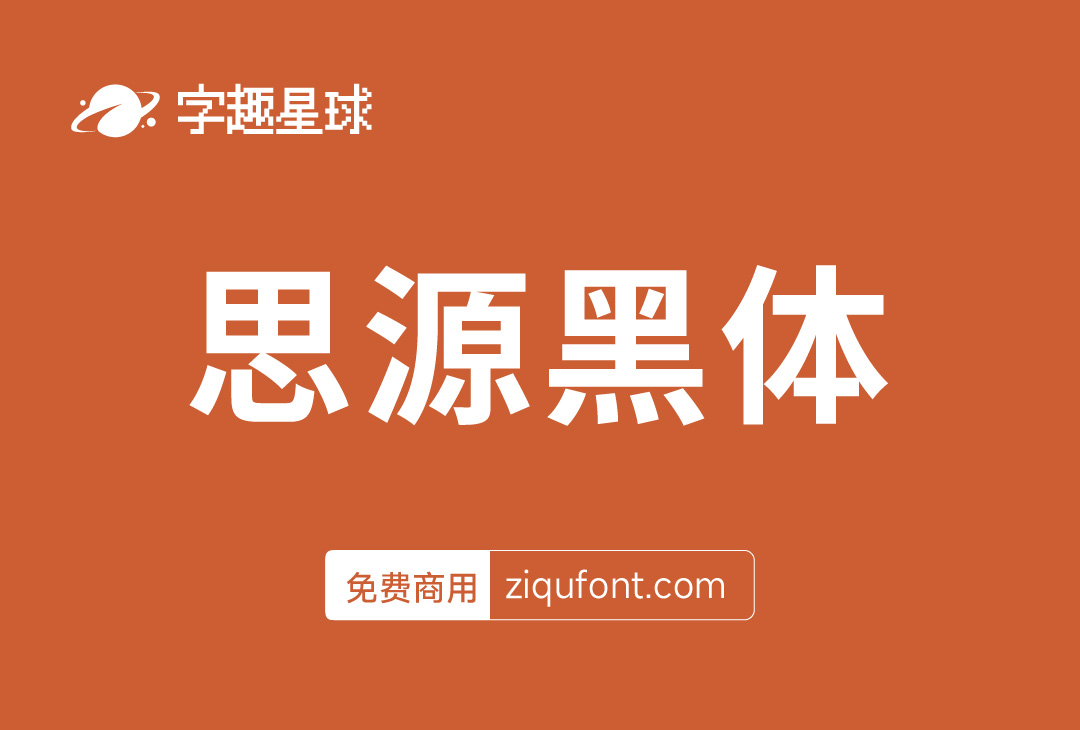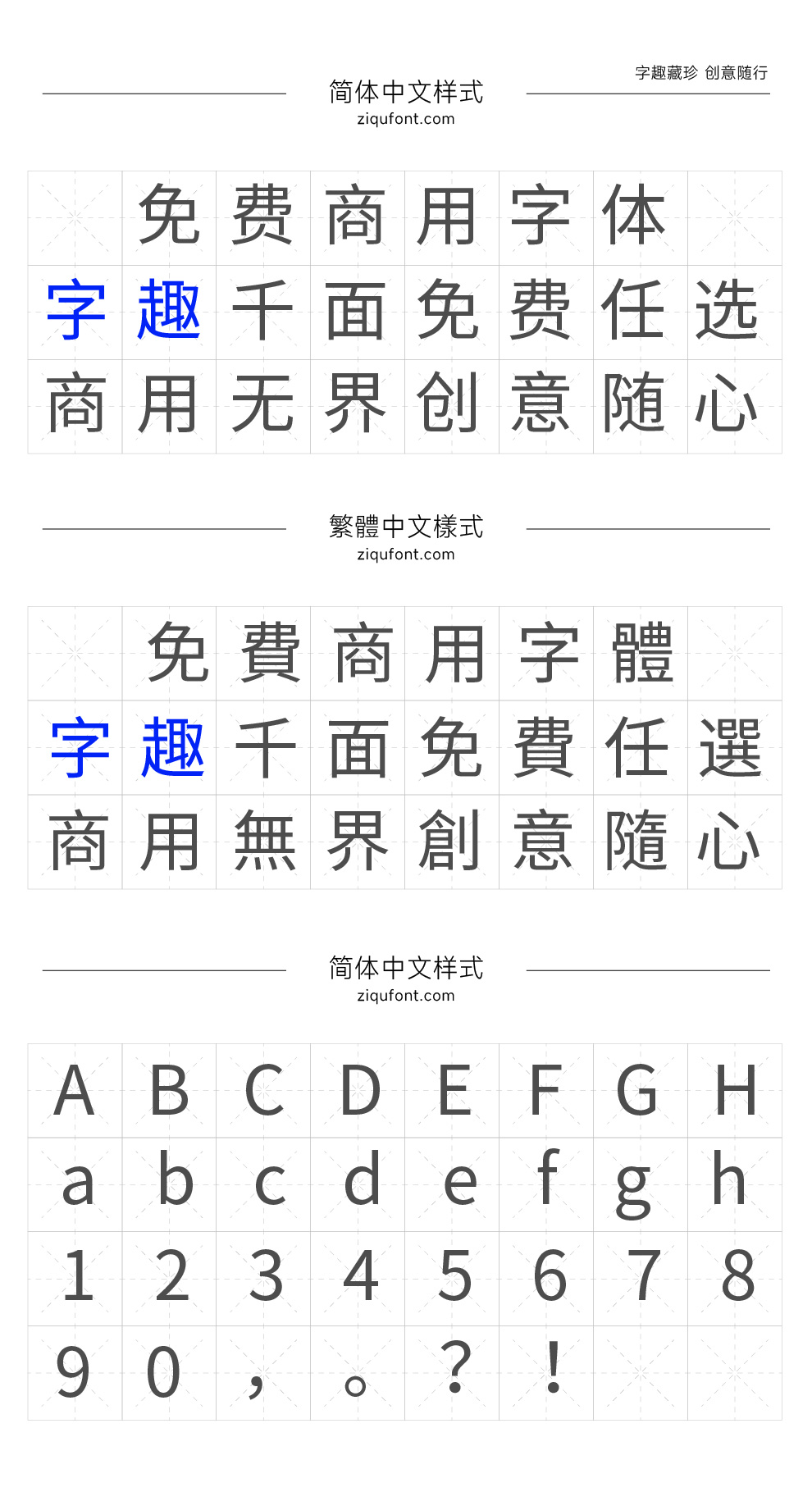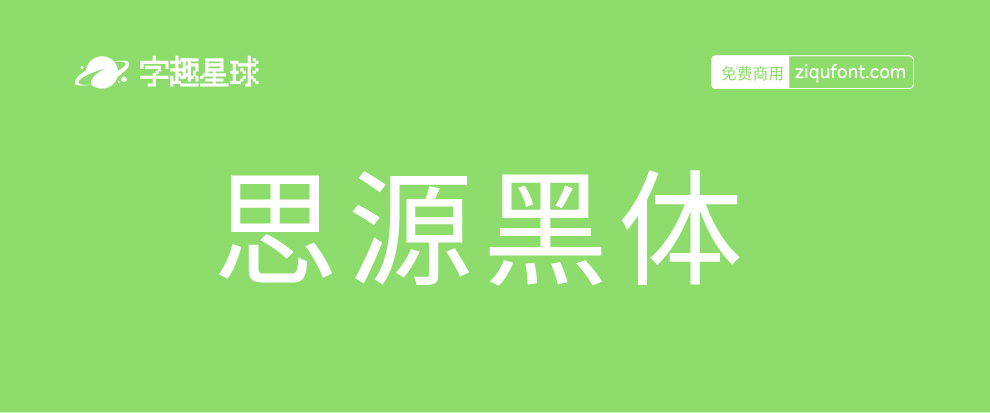
可变思源黑体来了!2.0版
思源黑体此次更新,支持了单个字重维度的可变字体格式。即在系统或软件的支持下,此版本思源黑体的粗细可以随意调节,有别于过往版本中固定的七个字重。
AI可变字体应用示例(仅支持2018及以上版本)
如上图所示PS/AI 2018以上版本的Adobe字体文件夹,预置了若干可变字体和彩色字体,可于软件中进行调用。
其中带有上图红框中下标“VAR”的字体,即为可变字体。在PS/AI 2018及以上版本中,可变字体相较于普通字体新增了调节滑块,拖动这些滑块就能直白的看出字体的变化。
除可变字体之外,思源黑体2.003笔画可供拆分,在AI中对字体进行扩展可以得到文字各部分的拼接笔画。
这样对字体进行修改会更为方便,目测接下来会有不少衍生X源字体应运而生。目前思源黑体只支持字重维度的形态变化,类似字宽、字高、倾角、倒角、衬线等维度还无法实现自由变换。